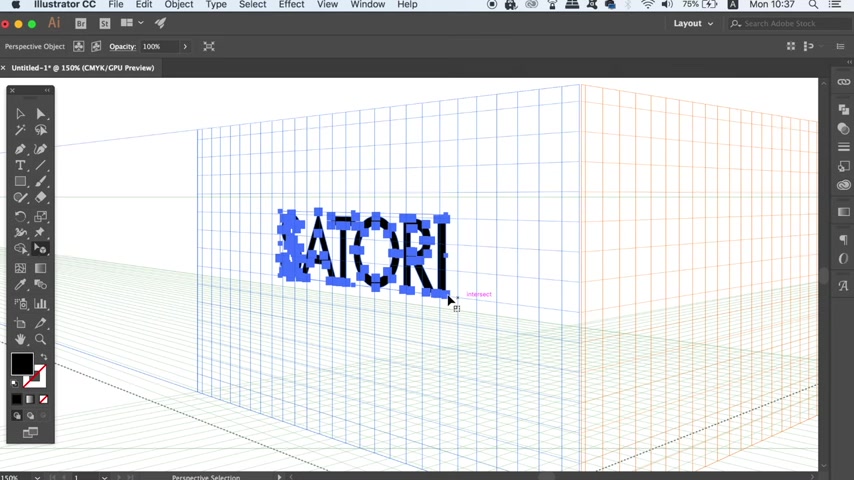
Perspektivische Typografie erstellen: Ein einfacher Illustrator Guide
In diesem umfassenden Illustrator Guide zeigen wir Ihnen, wie Sie beeindruckende perspektivische Typografie erstellen können, ohne auf komplizierte Warp-Tools oder mühsame manuelle Bearbeitungen zurückgreifen zu müssen. Dieser SEO-optimierte Artikel bietet Ihnen eine schrittweise Anleitung, um mit Adobe Illustrator in nur einem Klick professionelle Ergebnisse zu erzielen und Ihre Designs auf das nächste Level zu heben. Entdecken Sie, wie einfach es sein kann, Ihre kreativen Visionen in die Realität umzusetzen und die Aufmerksamkeit Ihrer Zielgruppe zu gewinnen.
Wesentliche Punkte
Schnelle Erstellung von perspektivischer Typografie in Adobe Illustrator.
Vermeidung von Warp-Tools und manuellen Perspektivkorrekturen.
Nutzung des Perspektivenrasters für präzise Ergebnisse.
Anpassung der Rastereinstellungen für individuelle Designs.
Einfaches Hinzufügen von Text und Formen zum Perspektivenraster.
Einführung in die perspektivische Typografie mit Adobe Illustrator
Was ist perspektivische Typografie?
Perspektivische Typografie ist eine Designtechnik, bei der Text so dargestellt wird, dass er in einem dreidimensionalen Raum zu existieren scheint. Dies verleiht dem Text Tiefe und Realismus, wodurch er visuell ansprechender und fesselnder wird. Diese Technik wird häufig in Logos, Postern und anderen grafischen Designs eingesetzt, um einen bleibenden Eindruck zu hinterlassen und die Aufmerksamkeit des Betrachters zu gewinnen. Durch die Anwendung von Perspektive auf Text kann man Illusionen von Tiefe, Raum und Bewegung erzeugen, die das Design dynamischer und interessanter machen. Perspektivische Typografie ist besonders nützlich, um Botschaften hervorzuheben und Designs einen professionellen und modernen Touch zu verleihen.
Die Bedeutung der perspektivischen Typografie im modernen Design liegt darin, dass sie es ermöglicht, Text auf eine Weise zu präsentieren, die über traditionelle, flache Darstellungen hinausgeht. In einer Welt, die von visuellen Reizen überflutet ist, kann die Verwendung von Perspektive dazu beitragen, dass ein Design hervorsticht und die Aufmerksamkeit der Zielgruppe auf sich zieht. Dies ist besonders wichtig in Bereichen wie Marketing und Werbung, wo der erste Eindruck entscheidend ist. Darüber hinaus kann perspektivische Typografie verwendet werden, um komplexe Ideen und Konzepte auf einfache und verständliche Weise zu vermitteln. Durch die Schaffung von räumlichen Beziehungen und visuellen Hierarchien kann man sicherstellen, dass die Botschaft klar und prägnant ist und beim Betrachter ankommt.
Es gibt verschiedene Arten der perspektivischen Typografie, darunter die Ein-Punkt-Perspektive, die Zwei-Punkt-Perspektive und die Drei-Punkt-Perspektive. Jede dieser Techniken bietet unterschiedliche Möglichkeiten, Tiefe und Realismus zu erzeugen, und die Wahl der richtigen Perspektive hängt von den spezifischen Anforderungen des Designs ab. In diesem Guide werden wir uns auf eine einfache Methode konzentrieren, um perspektivische Typografie in Adobe Illustrator zu erstellen, ohne auf komplexe Werkzeuge oder manuelle Anpassungen zurückgreifen zu müssen. Diese Methode ist ideal für Designer, die schnell und effizient professionelle Ergebnisse erzielen möchten.
Die Anwendungen der perspektivischen Typografie sind vielfältig und reichen von der Gestaltung von Logos und Markenidentitäten bis hin zur Erstellung von beeindruckenden visuellen Effekten in Postern und Werbekampagnen. Auch im Bereich der Webgestaltung kann diese Technik eingesetzt werden, um interaktive und immersive Erlebnisse zu schaffen, die die Benutzerbindung erhöhen. Kurz gesagt, perspektivische Typografie ist ein wertvolles Werkzeug für jeden Designer, der seine kreativen Möglichkeiten erweitern und Designs schaffen möchte, die im Gedächtnis bleiben.
Warum Adobe Illustrator für perspektivische Typografie?
Adobe Illustrator ist ein branchenführendes Vektor Grafikprogramm, das sich durch seine präzisen Werkzeuge und flexiblen Funktionen auszeichnet. Für die Erstellung perspektivischer Typografie bietet Illustrator eine Reihe von Vorteilen, die es zur idealen Wahl für Designer machen. Einer der größten Vorteile ist das Perspektivenraster-Werkzeug, das es ermöglicht, Objekte und Text einfach in einem dreidimensionalen Raum zu platzieren und zu verzerren. Dieses Werkzeug automatisiert viele der manuellen Schritte, die bei der Erstellung von Perspektive erforderlich sind, und spart so Zeit und Mühe.
Ein weiterer Vorteil von Illustrator ist seine nahtlose Integration mit anderen Adobe Creative Cloud Anwendungen wie Photoshop und InDesign. Dies ermöglicht es Designern, ihre perspektivische Typografie problemlos in andere Projekte zu integrieren und einen konsistenten visuellen Stil über verschiedene Medien hinweg zu gewährleisten. Darüber hinaus bietet Illustrator eine breite Palette von Typografie-Werkzeugen, mit denen man Text gestalten und anpassen kann, um den gewünschten Effekt zu erzielen. Von der Auswahl der richtigen Schriftart bis hin zur Anpassung der Kerning und Tracking-Einstellungen bietet Illustrator alles, was man benötigt, um beeindruckende Typografie zu erstellen.
Im Vergleich zu anderen Grafikprogrammen bietet Illustrator eine unübertroffene Präzision und Kontrolle über Vektor Grafik. Dies ist besonders wichtig bei der Erstellung perspektivischer Typografie, wo selbst kleinste Ungenauigkeiten das Endergebnis beeinträchtigen können. Mit Illustrator kann man sicherstellen, dass jede Linie und Kurve perfekt ausgerichtet ist und die Perspektive korrekt dargestellt wird. Darüber hinaus ist Illustrator ein nicht-destruktives Bearbeitungsprogramm, was bedeutet, dass man Änderungen an seinen Designs vornehmen kann, ohne die ursprünglichen Daten zu verlieren. Dies ist besonders nützlich bei der Erstellung perspektivischer Typografie, wo man möglicherweise verschiedene Variationen und Anpassungen ausprobieren möchte.
Die Benutzerfreundlichkeit von Adobe Illustrator ist ein weiterer wichtiger Faktor, der es zur idealen Wahl für perspektivische Typografie macht. Das Programm verfügt über eine intuitive Benutzeroberfläche und eine umfassende Dokumentation, die es auch Anfängern ermöglicht, schnell die Grundlagen zu erlernen und professionelle Ergebnisse zu erzielen. Darüber hinaus gibt es eine große Online-Community von Illustrator-Benutzern, die bereit sind, ihr Wissen und ihre Erfahrungen zu teilen und bei Problemen zu helfen. Dies macht es einfach, Hilfe und Inspiration zu finden und seine Fähigkeiten kontinuierlich zu verbessern.
Neben der perspektivischen Typografie gibt es eine Reihe anderer Designtechniken, mit denen Sie Ihre Typografie verbessern können. Dazu gehören: Kerning und Tracking: Kerning bezieht sich auf den Abstand zwischen einzelnen Buchstaben, während Tracking den gleichmäßigen Abstand zwischen allen Buchstaben in einem Wort oder einer Zeile betrifft. Die korrekte Anpassung dieser Einstellungen kann die Lesbarkeit und Ästhetik Ihrer Typografie erheblich verbessern. Hierarchie: Die Schaffung einer klaren Hierarchie in Ihrer Typografie hilft, die Aufmerksamkeit des Betrachters zu lenken und die Botschaft effektiv zu vermitteln. Verwenden Sie verschiedene Schriftgrößen, -stile und -farben, um wichtige Elemente hervorzuheben. Kontrast: Der Einsatz von Kontrast kann Ihre Typografie dynamischer und interessanter machen. Experimentieren Sie mit verschiedenen Schriftarten, -größen und -farben, um einen visuellen Kontrast zu erzeugen, der die Aufmerksamkeit auf sich zieht. Leerzeichen: Der bewusste Einsatz von Leerzeichen kann die Lesbarkeit Ihrer Typografie verbessern und ihr einen eleganten und professionellen Look verleihen. Achten Sie darauf, ausreichend Abstand zwischen Buchstaben, Wörtern und Zeilen zu lassen. Farbharmonie: Die Wahl der richtigen Farben für Ihre Typografie kann deren Wirkung erheblich beeinflussen. Verwenden Sie ein Farbschema, das zur Gesamtästhetik Ihres Designs passt und die Botschaft effektiv unterstützt. Indem Sie diese Designtechniken kombinieren, können Sie beeindruckende Typografie erstellen, die die Aufmerksamkeit Ihrer Zielgruppe auf sich zieht und im Gedächtnis bleibt.